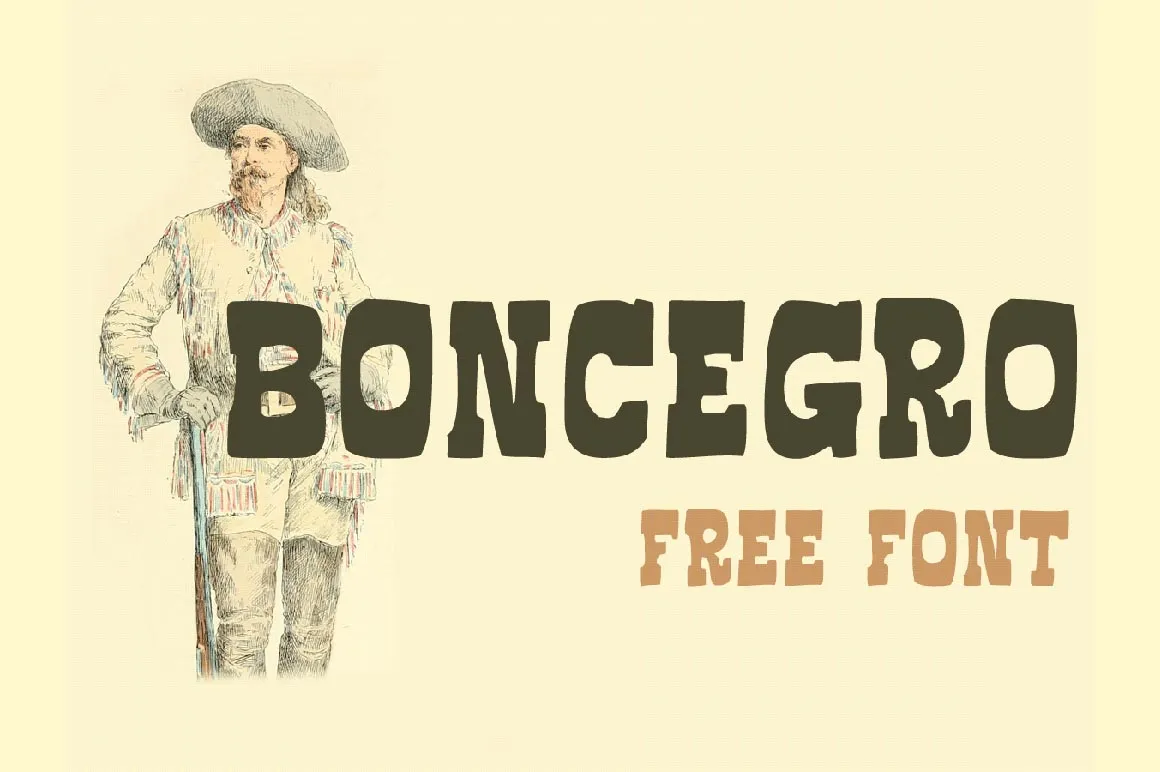
Boncegro Font – Fonte Grátis
Boncegro Font
A Boncegro Font é uma elegante tipografia serifada que evoca os belos estilos dos Estados Unidos do século XIX, com suas linhas fortes e traços delicados. Criada pelo designer Sergiy Tkachenko, essa fonte adquire um charme único através de sua mão-dura arte, projetando textos em um estilo chicoteado e elegante que combina perfeitamente para aplicações gráficas tanto no jornalismo visual quanto na publicidade impressa. Inspirada pela riqueza cultural dos tempos passados, a Boncegro é uma escolha inspiradora para qualquer projeto que busque transmitir um ar de história americana em sua identidade visual.